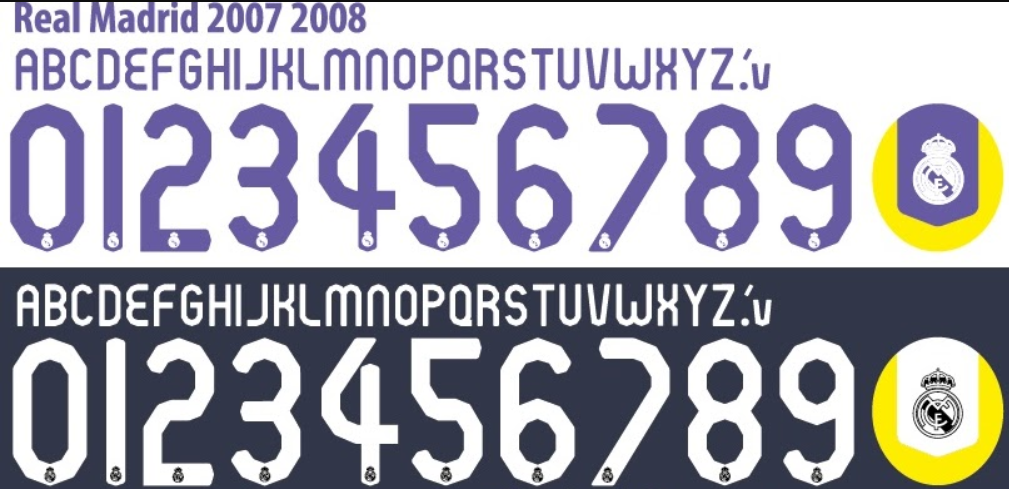
Se existe uma camisa que respira história, é o manto branco do Real Madrid. A temporada 2008-2009 marcou uma época de transição importante, onde lendas como Raúl, Casillas e Van Nistelrooy defendiam a honra dos Merengues nos gramados da Europa.
Estilo Visual e Aplicação
A tipografia de 2008-2009 da Adidas para o Real Madrid se destaca pela sua sobriedade e legibilidade. Diferente de fontes mais experimentais de anos posteriores, este estilo aposta em letras levemente condensadas e números robustos com bordas arredondadas, transmitindo uma sensação de estabilidade e classe.
Originalmente, os números aplicados nas camisas contavam com o escudo do clube discretamente posicionado na base, um detalhe que adicionava autenticidade ao uniforme. A fonte funciona perfeitamente tanto na camisa titular (branca com listras pretas) quanto no uniforme reserva (azul), mantendo o padrão de excelência visual da gigante alemã.
Dica de Design: Para um visual 100% fiel à época, utilize esta fonte apenas em caixa alta (maiúsculas), pois era assim que os nomes dos jogadores eram estampados na La Liga e na Champions League.